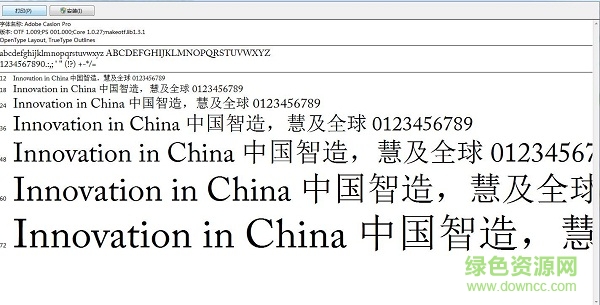
acaslonpro-regular
acaslonpro-regular字體是一款由adobe公司推出的經(jīng)典襯線字體,字面干凈,襯線裝飾漂亮,實(shí)用性強(qiáng),用在廣告設(shè)計(jì)、期刊雜志方面非常賞心悅目,歡迎大家免費(fèi)下載!
acaslonpro-regular